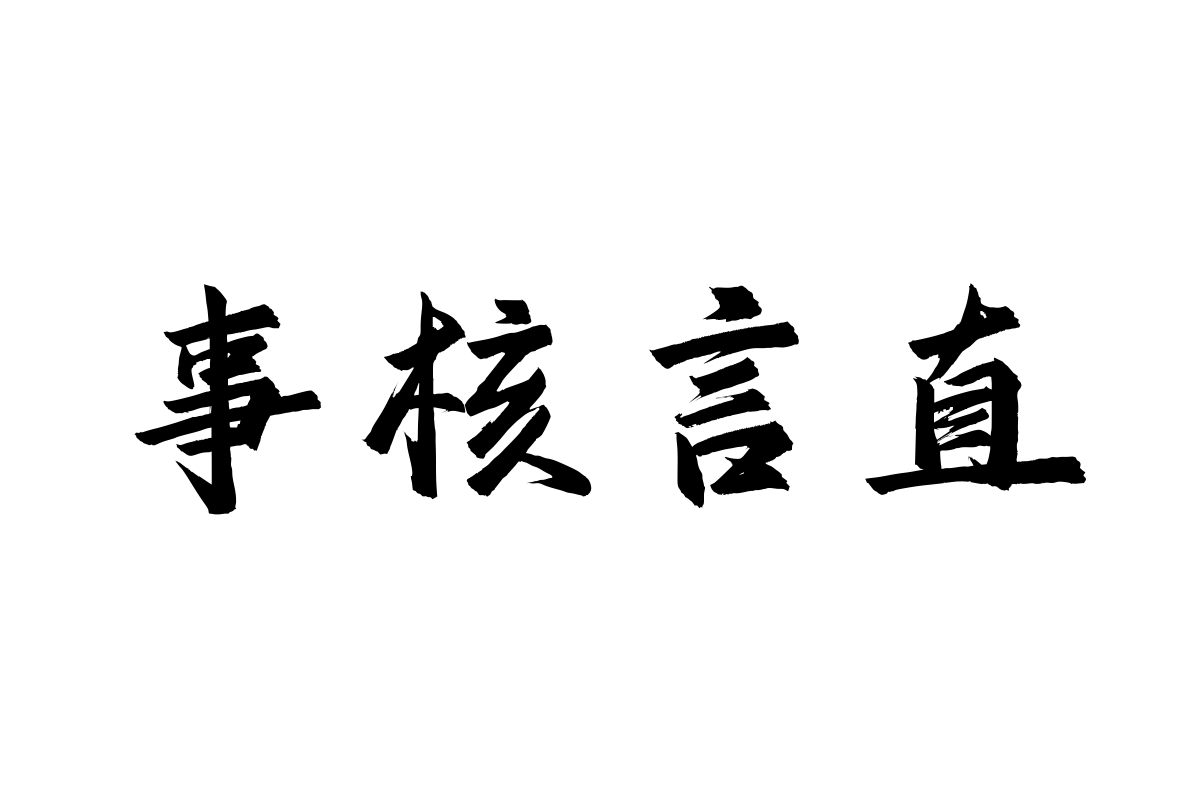
汉仪花木兰是一款具有独特韵味的字体,它以优雅、大方为特点,适合用于各种商业和设计场合。这款字体的设计灵感来源于中国传统的木兰形象,通过巧妙的笔画组合和结构布局,展现出了其独特的美感。
汉仪花木兰字体的特点主要体现在以下几个方面:
1. 字形优美:汉仪花木兰字体的字形线条流畅,结构严谨,给人一种优雅、大方的感觉。无论是横排还是竖排,都能呈现出良好的视觉效果。
2. 风格独特:汉仪花木兰字体的设计灵感来源于中国的传统木兰形象,因此它在字形上具有一定的民族特色。这种独特的风格使得汉仪花木兰字体在众多字体中脱颖而出,具有较高的辨识度。
3. 适用广泛:汉仪花木兰字体适用于各种商业和设计场合,如广告、海报、包装等。它的优雅、大方的特点使得它在这些场合中能够更好地展示出产品或品牌的特质。
4. 易于使用:汉仪花木兰字体具有良好的可读性和易用性,无论是在电脑屏幕上还是在印刷品上,都能够清晰地展现其优美的字形。这使得用户在使用时能够轻松地感受到这款字体的魅力。
总之,汉仪花木兰字体是一款具有独特韵味的字体,它的优雅、大方等特点使其在商业和设计领域中得到了广泛的应用。无论是用于文字排版还是图形设计,汉仪花木兰字体都能为用户带来美好的视觉体验。